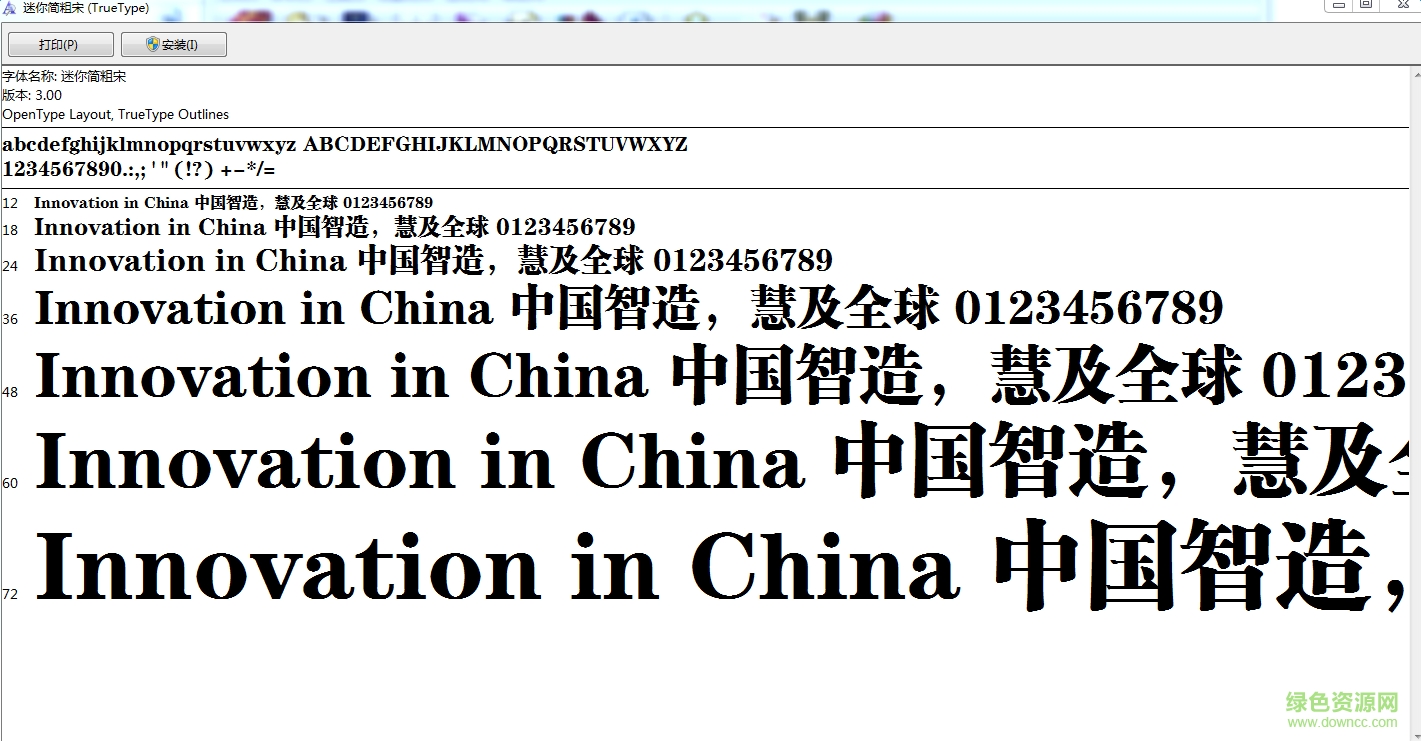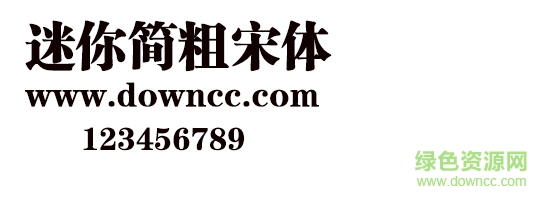
迷你簡粗宋字體是迷你字體庫推出的免費(fèi)字體文件。本字體為粗體風(fēng)格,在印刷、商標(biāo)設(shè)計(jì)以及廣告設(shè)計(jì)方面使用的比較多!有需要的用戶歡迎來綠色資源網(wǎng)下載使用。
迷你簡粗宋字體是一款簡約風(fēng)格的黑體字,字體效果比較黑,字體較粗,配上宋體風(fēng)格,給人非常舒服的感覺,還有更多好看字體盡情期待,喜歡粗體字的朋友可以下載使用看看效果如何。